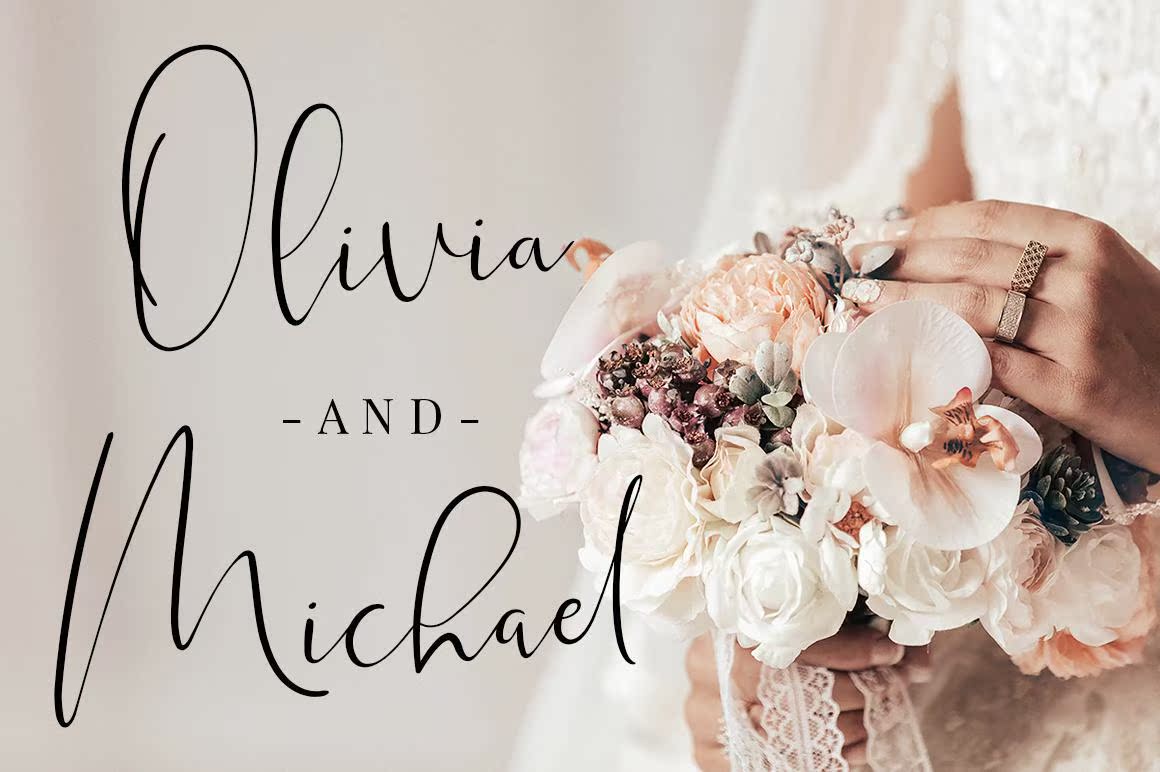
介绍新的SweetMadelyn scriptfont–时尚奢华的全新手写字体。此字体是品牌的完美选择。使用此字体,您将无法获得可爱、异想天开、有趣的标识。只有高端、高档、精致的品牌设计。介绍新的SweetMadelyn scriptfont–时尚,奢华、超级炫酷的全新手写字体。此字体是品牌的完美选择。使用此字体,您将无法获得可爱、异想天开、有趣的标识。只有高端、高档、精致的品牌设计。